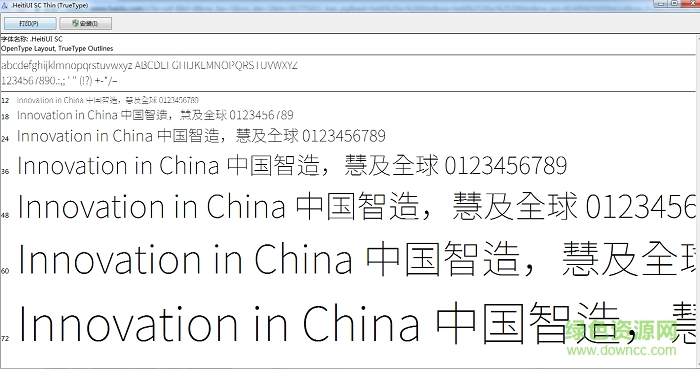
heiti sc thin字體是一款漂亮的黑體細(xì)體字體,線(xiàn)條纖細(xì)清晰,給人一種輕盈明快的感覺(jué),用在女性化妝品、雜志等廣告設(shè)計(jì)方面非常適合,感興趣的朋友快來(lái)下載吧!
黑體比較端莊嚴(yán)肅、筆畫(huà)簡(jiǎn)單、結(jié)構(gòu)嚴(yán)謹(jǐn)、引人注目、具有渾厚凝重的氣氛,是印刷界中較為穩(wěn)重、醒目的標(biāo)題字,實(shí)用性很強(qiáng)。